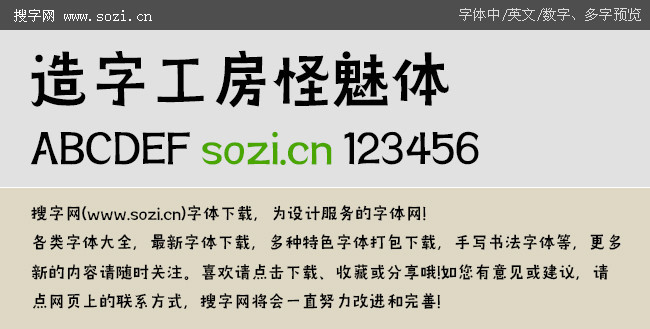
造字工房怪魅體
搜字網(wǎng)給大家提供一款造字工房怪魅體中文字體下載,造字工房怪魅字體融合綜藝體及哥特體風(fēng)格,結(jié)體奇崛,以拙寓巧,以樸寓華,率真質(zhì)樸,卡通可愛。適用于大標(biāo)題、包裝設(shè)計(jì)、海報(bào)設(shè)計(jì)等應(yīng)用。(本字體為個(gè)人非商用版,如需要商用請(qǐng)聯(lián)系官方購買版權(quán))